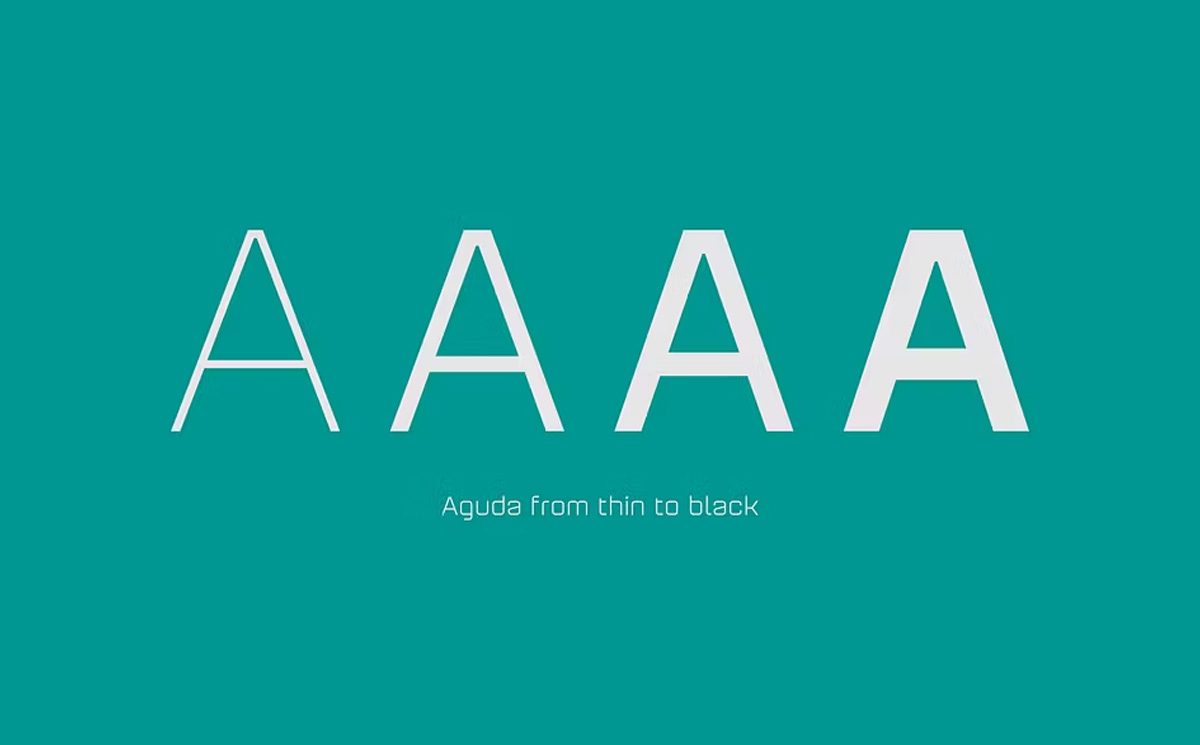
Font Chữ Cứng Cáp Miễn Phí SVN Aguda | Thiết Kế Hiện Đại & Tối Giản
Khám phá SVN Aguda, bộ font chữ cứng cáp, miễn phí, Việt hóa hoàn hảo bởi nhóm STYLEno.1 Fonts. Phù hợp cho thiết kế display, poster, công nghệ và branding tối giản. Tải ngay bộ phông chữ sans serif hình học hiện đại này.
Font Chữ Cứng Cáp Miễn Phí SVN Aguda: Sức Mạnh Đến Từ Thiết Kế Mô-đun & Hình Học
Trong thế giới typography, việc tìm kiếm một bộ phông chữ vừa mang lại cảm giác “cứng cáp,” mạnh mẽ, lại vừa đảm bảo sự hiện đại và Việt hóa chuẩn xác là một thách thức đối với nhiều designer.
Font chữ SVN-Aguda chính là lời giải hoàn hảo cho bài toán này. Được Việt hóa tỉ mỉ bởi đội ngũ STYLEno.1 Fonts từ phông chữ gốc Aguda của nhà thiết kế Pablo Balcells, bộ font này đã nhanh chóng trở thành một “vũ khí” đắc lực trong tay các nhà thiết kế Việt Nam yêu thích phong cách tối giản và hiện đại.
Bài viết này sẽ đi sâu vào nguồn gốc, đặc điểm thiết kế và những ứng dụng thực tế đỉnh cao của SVN Aguda.
Nguồn Gốc và Đặc Điểm Thiết Kế Của SVN-Aguda
1. Xuất Thân “Trâm Anh Thế Phiệt”
Phông chữ gốc Aguda được nhà thiết kế tài năng Pablo Balcells thiết kế vào năm 2014 cho Graviton Font Foundry. Aguda được biết đến là một typeface mang đậm tính mô-đun và hình học (geometric sans-serif).
2. Định Nghĩa “Cứng Cáp” Bằng Typography
Sự “cứng cáp” của SVN Aguda không đến từ các nét dày đặc biệt của nhóm slab-serif (chữ có chân lớn), mà đến từ cấu trúc modular của nó. Các ký tự được xây dựng dựa trên các dạng hình học cơ bản lặp đi lặp lại, tạo ra sự đồng nhất, dứt khoát và cảm giác cơ khí mạnh mẽ.
Các góc bo được tính toán chính xác để giữ lại sự sắc sảo nhưng không làm người xem cảm thấy quá thô cứng.
Tại Sao Font SVN-Aguda Lại Được Ưa Chuộng Tại Việt Nam?
Bộ font này hội tụ đầy đủ các yếu tố để “làm mưa làm gió” trong cộng đồng thiết kế Việt.
Ưu điểm Mô tả
Thiết Kế “Display” Đỉnh Cao SVN Aguda được định hướng chủ yếu cho mục đích trình bày (display typeface). Nó làm tốt nhất nhiệm vụ thu hút sự chú ý khi được sử dụng ở kích thước lớn.
Việt Hóa “Chính Chủ” SVN Nhóm STYLEno.1 Fonts nổi tiếng với những bản Việt hóa chất lượng cao. Các dấu tiếng Việt của SVN Aguda được đặt chính xác, cân đối, không lỗi kerning, giúp designer yên tâm sử dụng.
Độ Rõ Nét (Readability) Cao Mặc dù là font display, Aguda sở hữu cấu trúc rất rõ ràng. Nó cũng có thể được sử dụng hiệu quả cho các đoạn văn bản ngắn và trung bình mà không gây mỏi mắt.
Bản “VIP” Với 4 Kiểu Chữ Phiên bản Việt hóa SVN Aguda thường được chia sẻ với 4 kiểu chữ cơ bản (ví dụ: Regular, Bold, v.v.), cung cấp đủ sự linh hoạt cho các bố cục thiết kế.
Các Ứng Dụng Đỉnh Cao Của SVN-Aguda Trong Thiết Kế
SVN Aguda là một lựa chọn lý tưởng cho các ngành cần sự mạnh mẽ, công nghệ, và hiện đại.
H3: Poster, Thumbnail và Headline
Đây là “sân chơi” chính của SVN Aguda. Nhờ sự cứng cáp và dứt khoát, nó giúp tên sự kiện, tiêu đề video YouTube, hay headline của bài đăng social media trở nên nổi bật ngay lập tức. Phù hợp cho poster phim hành động, sự kiện thể thao, công nghệ.
Thiết Kế Branding & Logo (Minimalist)
SVN Aguda rất lý tưởng để thiết kế logo cho các công ty công nghệ, xây dựng, kiến trúc, ô tô hoặc các thương hiệu hướng tới vẻ ngoài mạnh mẽ, bền vững và tối giản.
Bao Bì Sản Phẩm & Nhãn Mác
Dùng cho tiêu đề sản phẩm trên bao bì, đặc biệt là các sản phẩm công nghệ, đồ gia dụng cơ khí, tạo cảm giác tin cậy và có độ bền cao.
Giao Diện Web & App (UI/UX)
Sử dụng cho các tiêu đề lớn của website công nghệ, trang landing page hoặc các phần tử cần điểm nhấn mạnh mẽ trong giao diện ứng dụng di động.
Kết Luận
Font chữ cứng cáp SVN Aguda là một sự lựa chọn tuyệt vời cho designer cần một phông chữ mạnh mẽ, hiện đại, tối giản và Việt hóa hoàn hảo. Sự kết hợp giữa thiết kế mô-đun dứt khoát và chất lượng Việt hóa VIP từ STYLEno.1 Fonts khiến nó trở thành một phông chữ “phải có” trong bộ sưu tập.